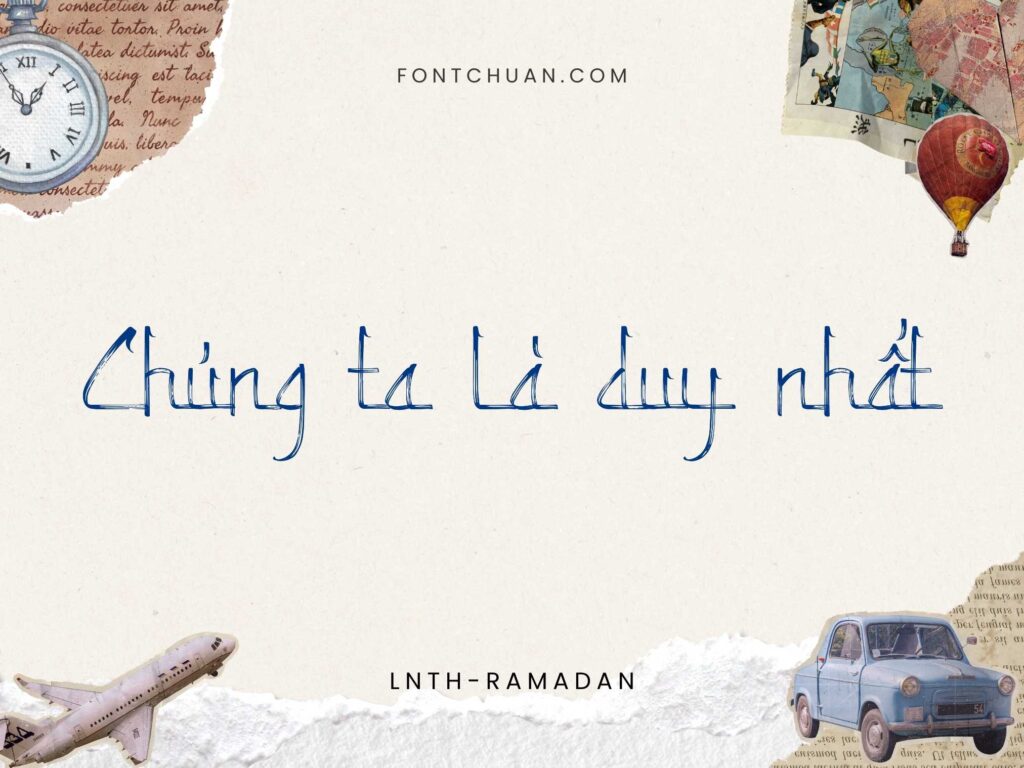
Font LNTH Ramadan Việt Hóa
Font Ramadan là một kiểu chữ trang trí mang phong cách Hồi giáo, được thiết kế với các đường nét hoa văn tinh xảo, gợi nhớ đến nghệ thuật kiến trúc Ả Rập và những nét đẹp truyền thống trong tháng lễ Ramadan. Với các ký tự có độ uốn lượn đặc trưng, font này mang đến cảm giác thanh lịch, huyền bí và trang trọng, rất phù hợp với các thiết kế mang phong cách tôn giáo, văn hóa hoặc sự kiện lễ hội
Phiên bản này đã được Việt hóa bởi LNTH, hỗ trợ đầy đủ tiếng Việt cùng hơn 50 ngôn ngữ khác, giúp người dùng dễ dàng ứng dụng trong thiết kế quốc tế. Font Ramadan được các thành viên Font Chuẩn sưu tầm và đăng tải nhằm mang đến một lựa chọn đặc sắc dành cho những ai yêu thích phong cách typography truyền thống và tinh tế
Về đặc điểm thiết kế, Ramadan có các đường nét thanh mảnh nhưng sắc sảo, kết hợp với các họa tiết đặc trưng, tạo nên sự sang trọng và hoài cổ. Kiểu chữ này rất phù hợp để sử dụng trong thiết kế banner, thiệp mời, ấn phẩm tôn giáo hoặc các thiết kế mang tính truyền thống
Font Ramadan được ứng dụng rộng rãi trong các sự kiện như lễ hội tôn giáo, Ramadan, thiết kế mang phong cách văn hóa Trung Đông. Nó phù hợp với nhiều ngành nghề như quảng cáo, bất động sản, giáo dục, công nghệ